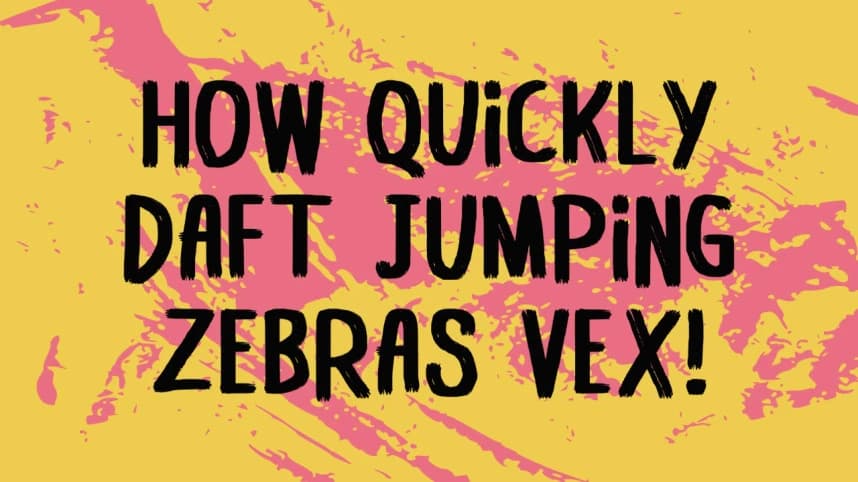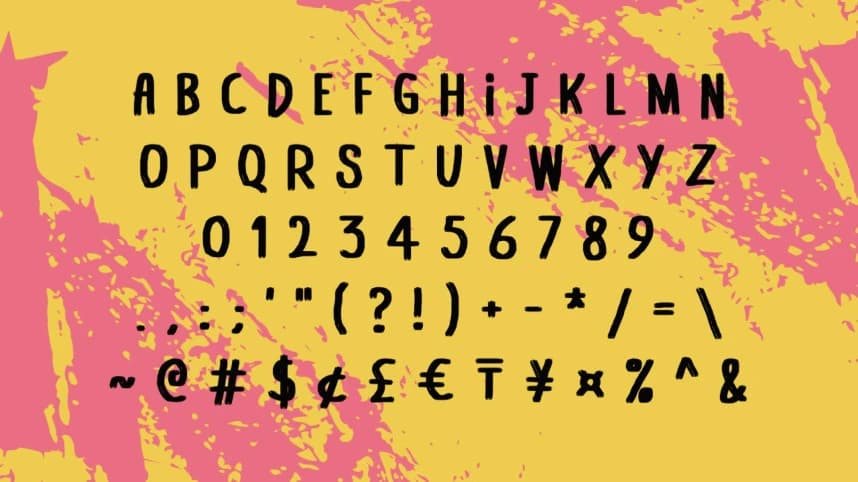
Drybrush Yazı Tipi
Drybrush Font, gerçek kuru fırça yazı tipinin dokusu ve hareketini yakalayan ifade gücü yüksek bir fırça yazı tipidir. Pürüzlü, izli vuruşlar yazı tipine doğal olarak aşınmış bir görünüm kazandırır; görünen taneler ve kırık kenarlar her karaktere derinlik ve enerji katar.
Drybrush Font, gerçek kuru fırça yazı karakterinin dokusunu ve hareketini yakalayan ifadeli bir fırça yazı tipidir. Kaba, çizgili vuruşlar tipografiye doğal olarak yıpranmış bir görünüm kazandırır; görülebilir taneli doku ve kırık kenarlar her karaktere derinlik ve enerji katar.